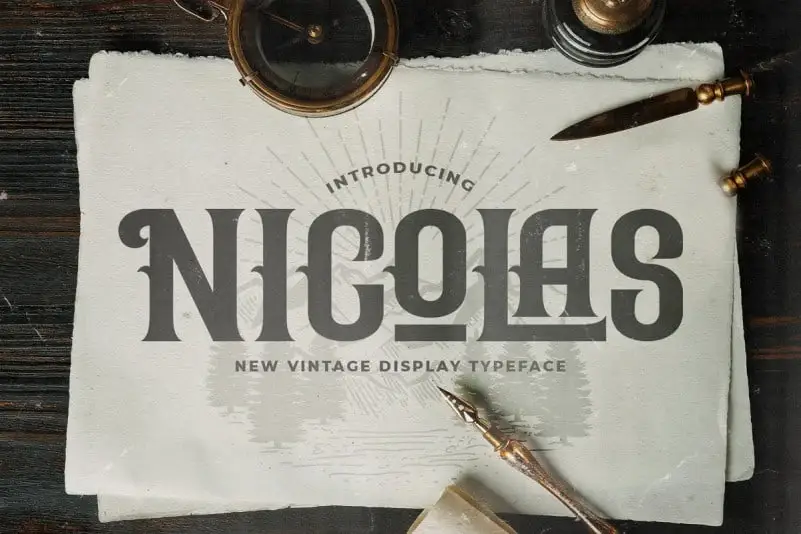
A Nicolas Display Font é uma fonte inspirada nas famosas tipografias clássicas com um estilo retro vibrante. Ela foi criada pelo StringLabs e agora está disponível para download. Esta fonte é perfeita para projetos que exigem um look fashion, como roupas ou moda de consumo; também funciona maravilhosamente em capas de álbuns, logotipos, marcações, revistas, mídias sociais e anúncios. Seus traços curtos e aprimorados garantem que você possa usar esta fonte para tornar seus projetos ainda mais chamativos e modernos. Sem dúvida, uma escolha ideal tanto para designers de moda quanto para designers gráficos em geral.